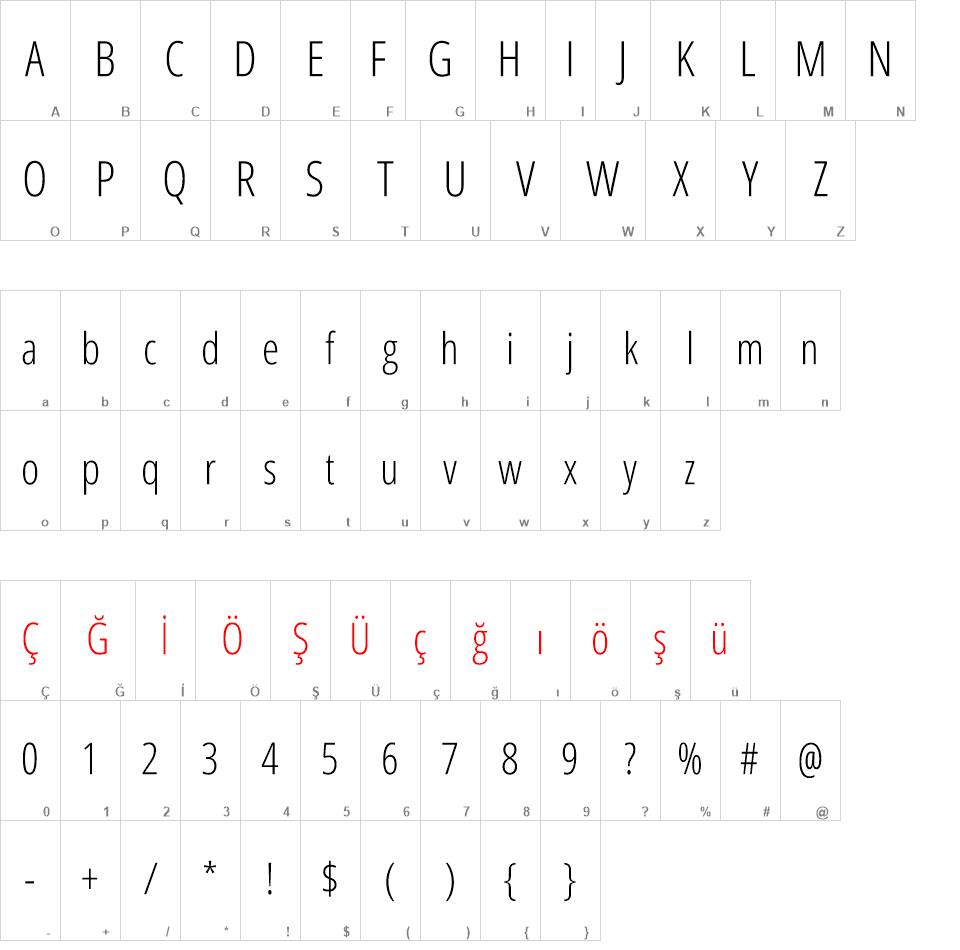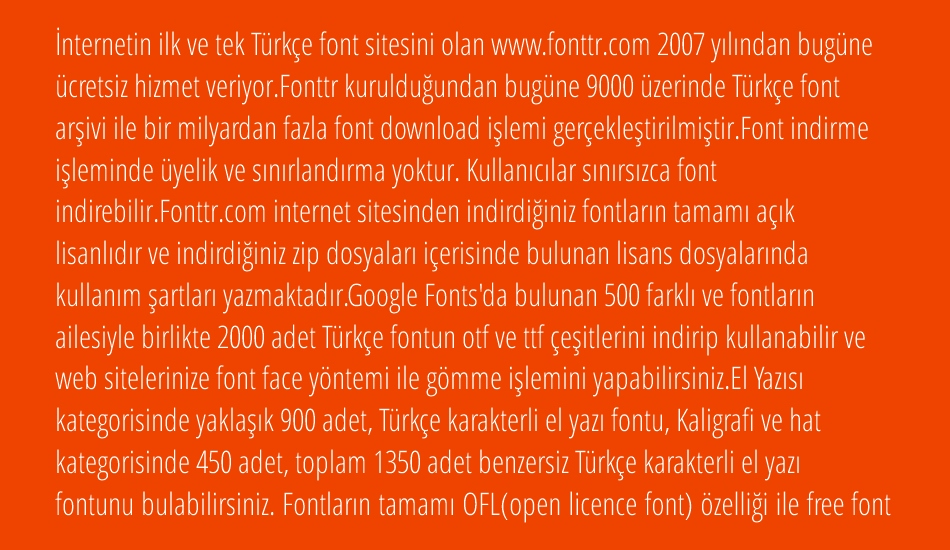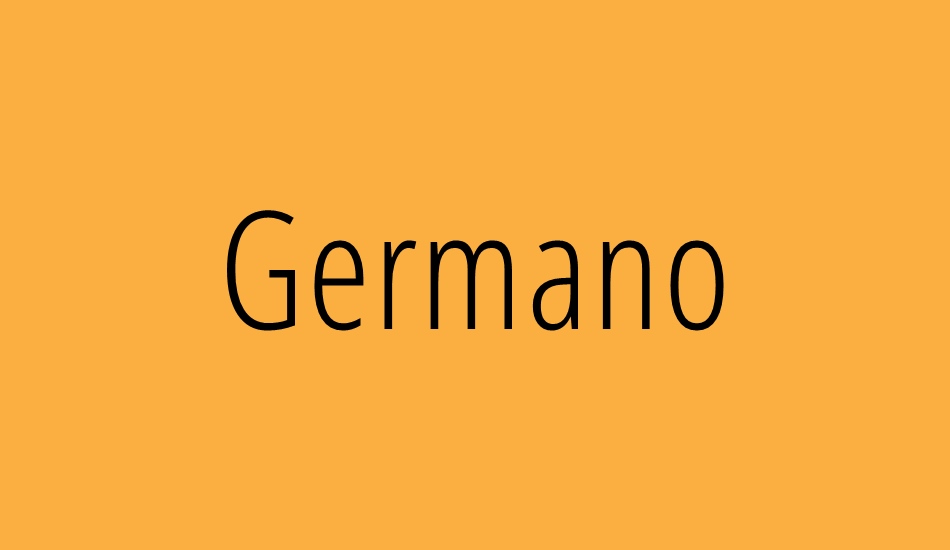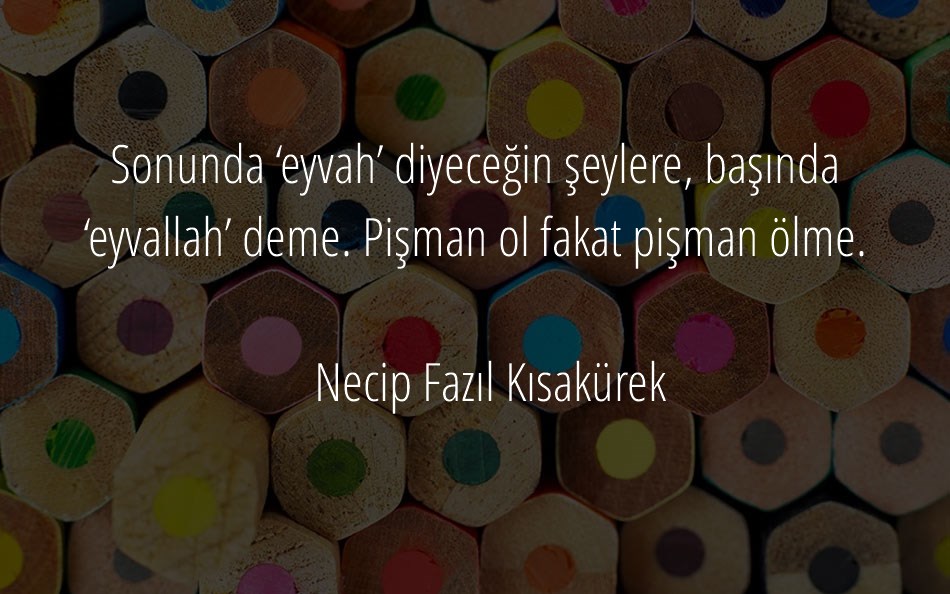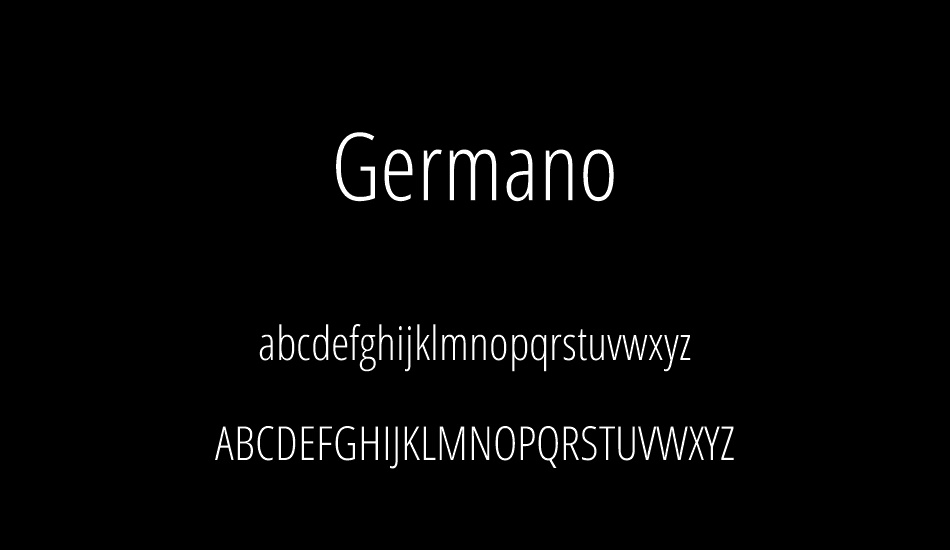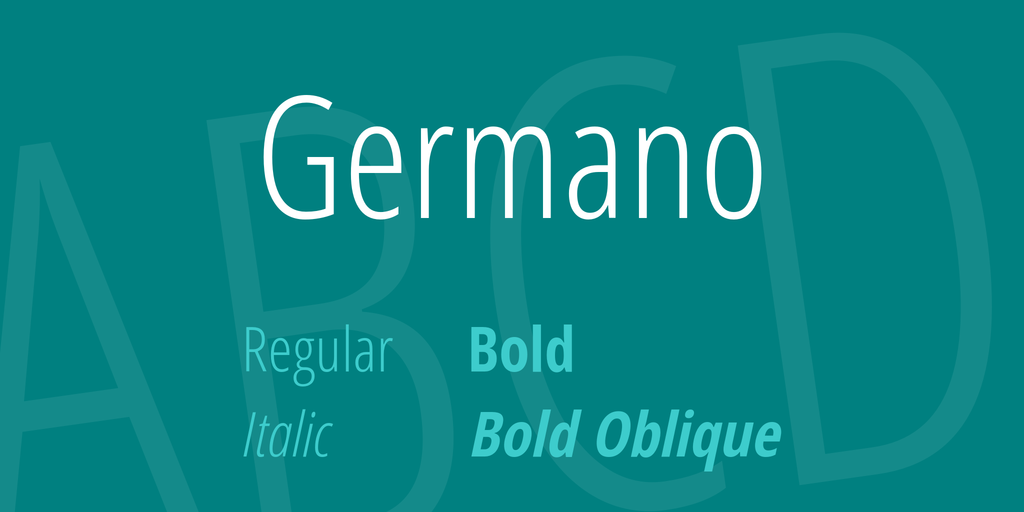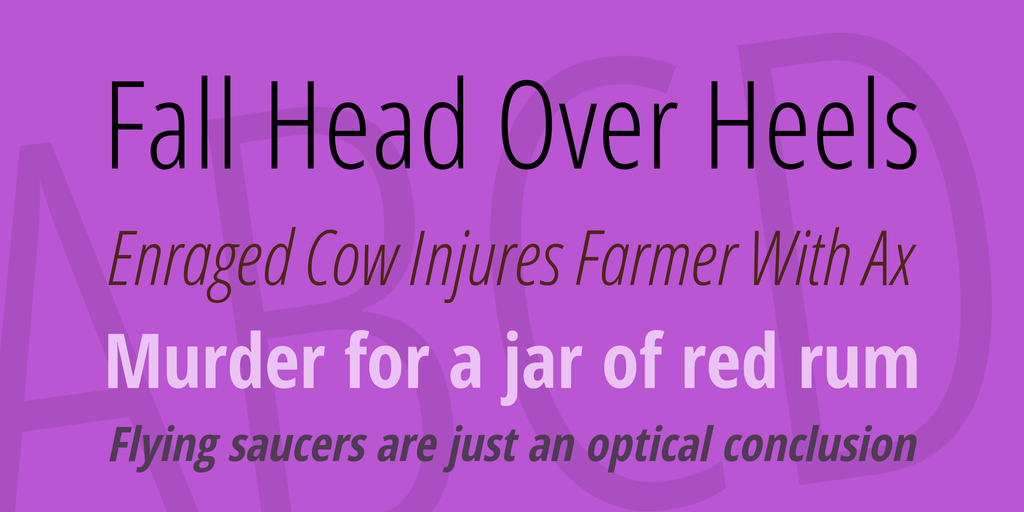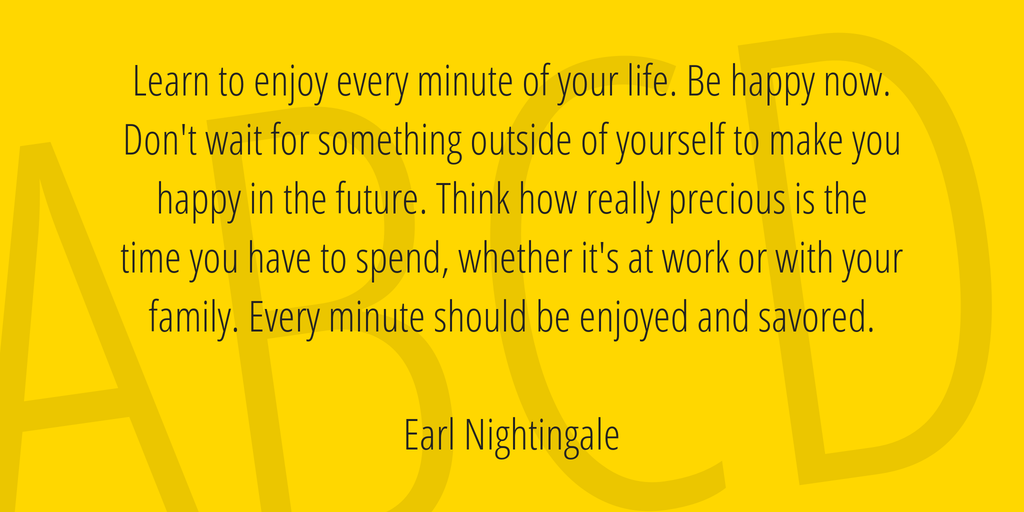
Germano Font Family font
Germano, BoldOblique Yazı biçimi eklenerek Steve Matteson tarafından Yoğunlaştırılmış Açık Sans'a dayanıyor. Açık Sans Sıkıştırılmış, bence tüm zamanların en büyük özlü yazı biçiminden biridir. Ne yazık ki, bazı problemleri var, bu yüzden Germano'yu yarattım. Güncelleme: Şimdi, bu zip arşivinde @ font-face paketinin tamamı geliyor.